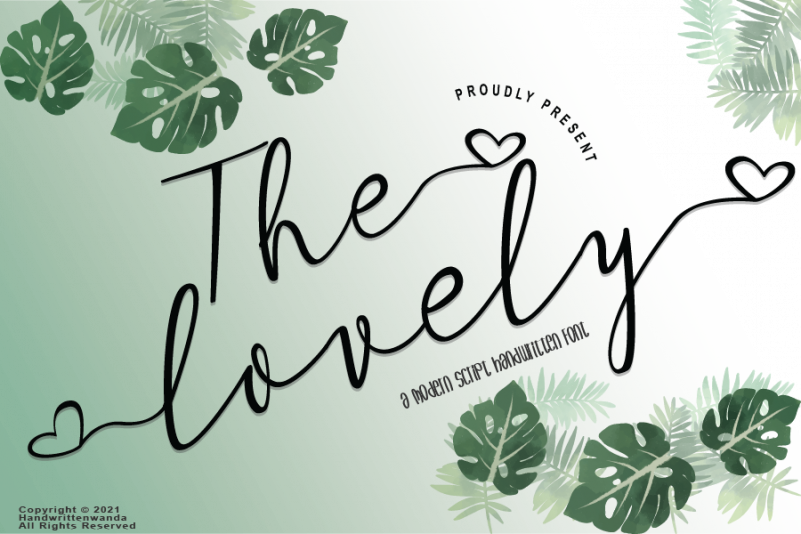
The Lovely Font – Fonte Grátis
The Lovely Font
A fonte ‘The Lovely Font’ é uma elegante tipografia script, perfeitamente equilibrada e refinada que transpira sofisticação e elegância. Suas alternativas estilizadas e ligaturas criam um conjunto harmônico que se ajusta com maestria a qualquer projeto. Esta fonte é ideal para designers que desejam adicionar uma aparente delicadeza e sofisticação à suas criações, seja em cartazes publicitários, gráficos de e-mail ou qualquer aplicação visual. A designer handwrittenwanda criou um estilo único nesta tipografia, proporcionando ao seu público a oportunidade de incorporar elementos pessoais e únicos que trazem vida e personalidade para seus projetos. ‘The Lovely Font’ é uma escolha perfeita para quem valoriza uma combinação harmônica entre modernidade e elegância, sem perder o toque delicado característico das fuentes escritas à mão.